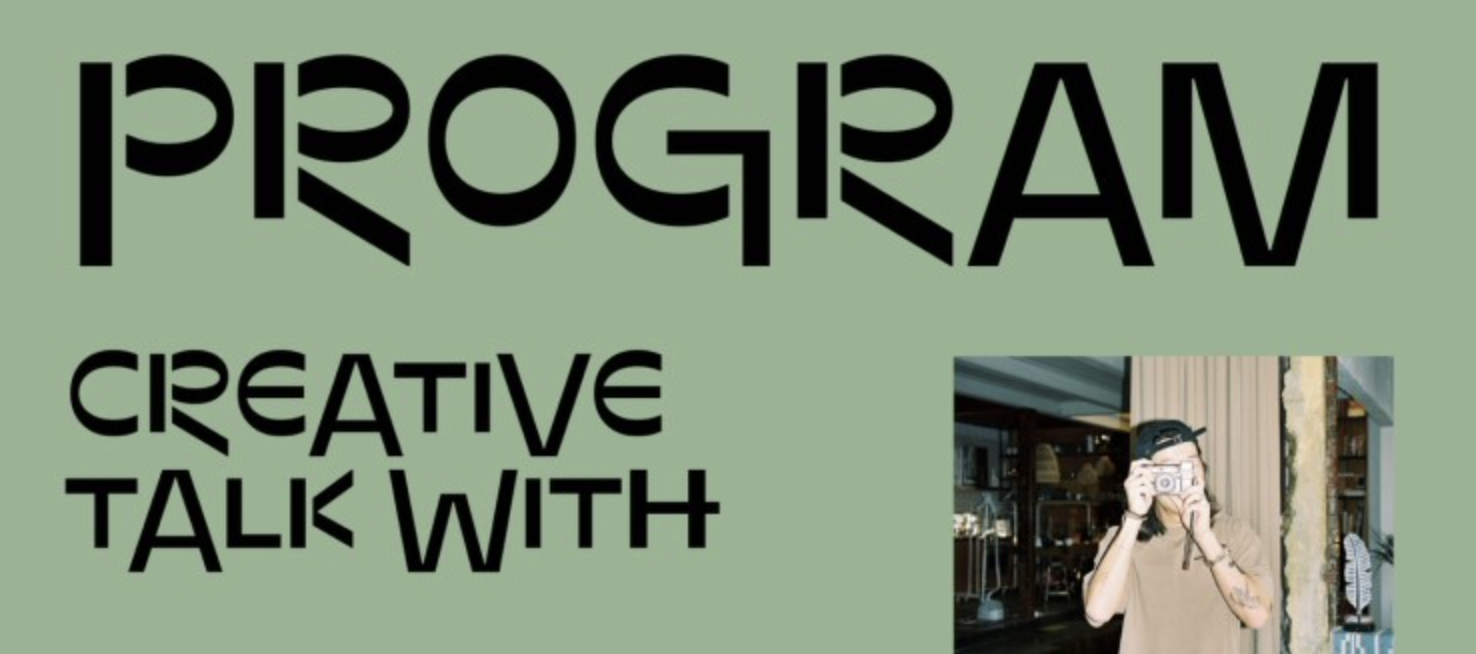
이 귀여운 폰트 아시나요? ico*** 2024.01.31 이 폰트가 궁금합니다 너무 귀엽고 특이해서요. 댓글 0 등록 떼이큣 Brutal 폰트 같아요! https://www.myfonts.com/collections/brutal-font-benbenworld/ 2024-02-02 답글 달기 댓글 더보기 쉽고 빠르게 가장 비슷한 폰트를 알고 싶다면? 이미지로 검색하기
Brutal 폰트 같아요! https://www.myfonts.com/collections/brutal-font-benbenworld/